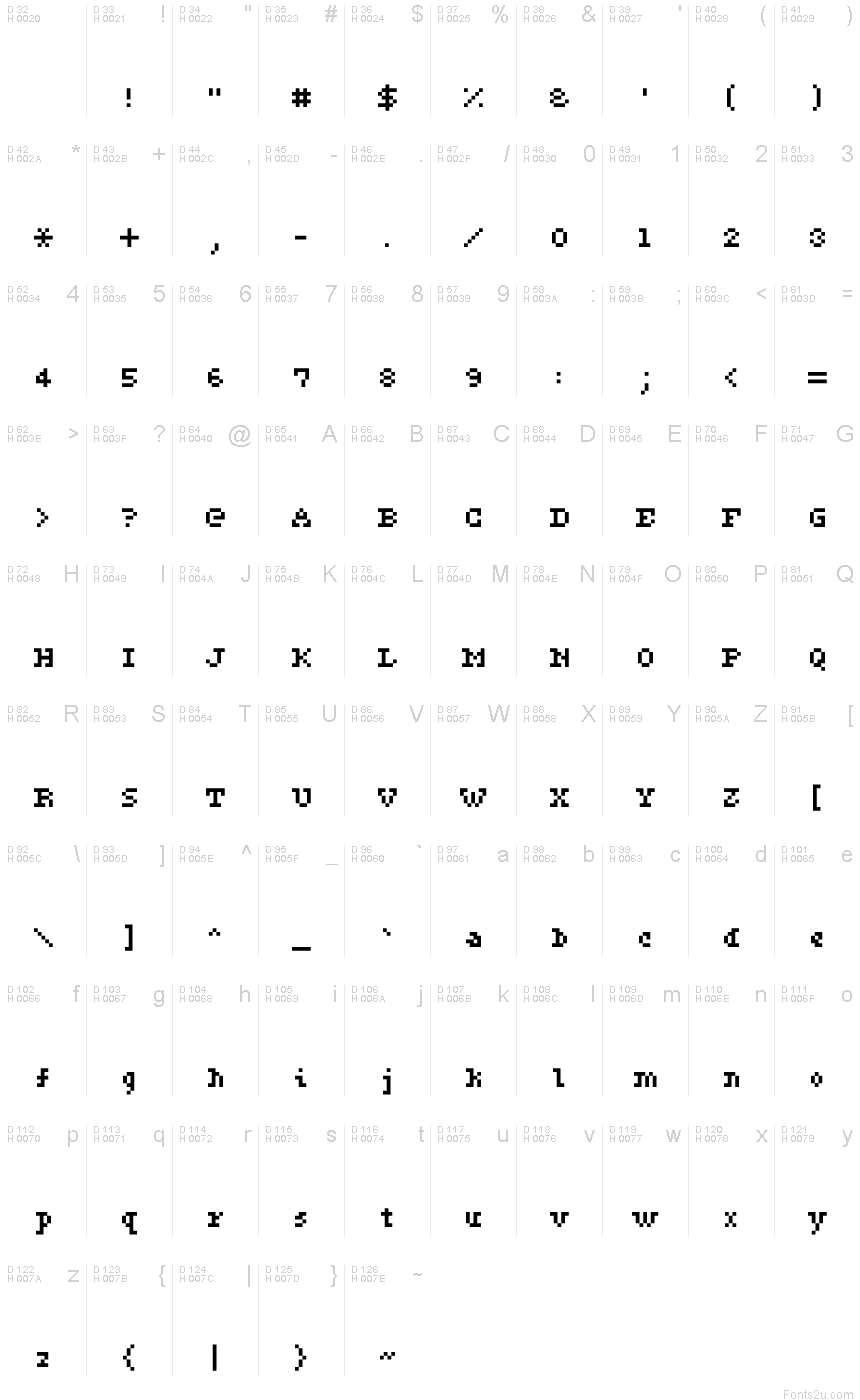
Ceriph 05 56 autorstwa Craiga Kroegera to darmowy krój bitmapowy o suchym klimacie wczesnych ekranów. Litery zbudowane są z grubych, kwadratowych pikseli, ale drobne, przypominające szeryfy detale i stopniowane łączenia sprawiają, że nie wygląda on czysto utylitarnie, nadając krojowi bezpośredni, nieco dziwaczny, redakcyjny charakter.
Sprawdzi się wszędzie tam, gdzie retro-interfejs potrzebuje ostrzejszego sznytu – fanziny, menu gier, plakaty, grafiki internetowe i napisy tytułowe świetnie pasują do tego darmowego fontu. Ponieważ szeryfowe akcenty przetrwały wewnątrz siatki, krój dobrze radzi sobie również w krótkich nagłówkach i logotypach, które chcą uzyskać pikselową ziarnistość, nie popadając w wygląd prostego kroju terminalowego.